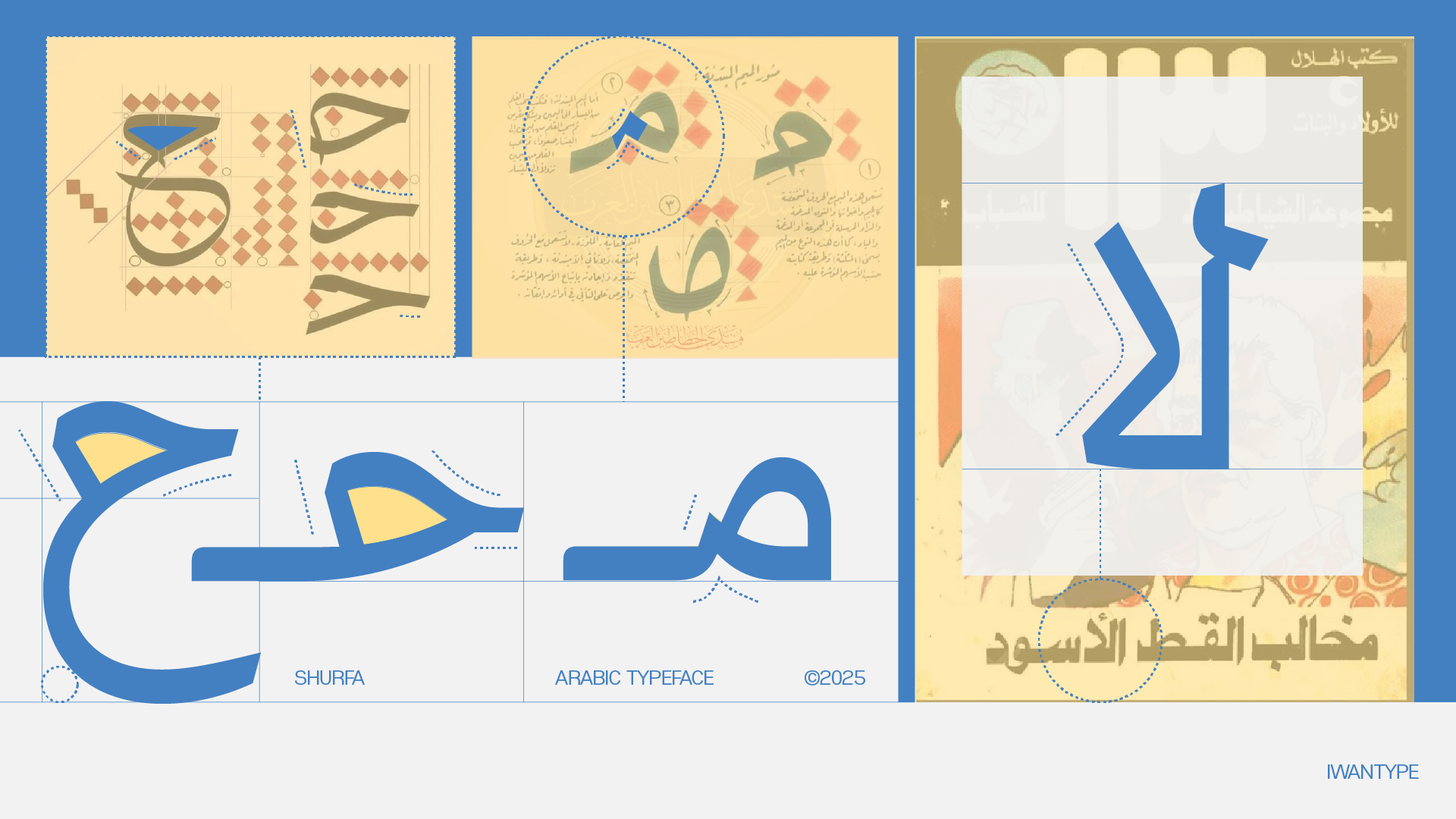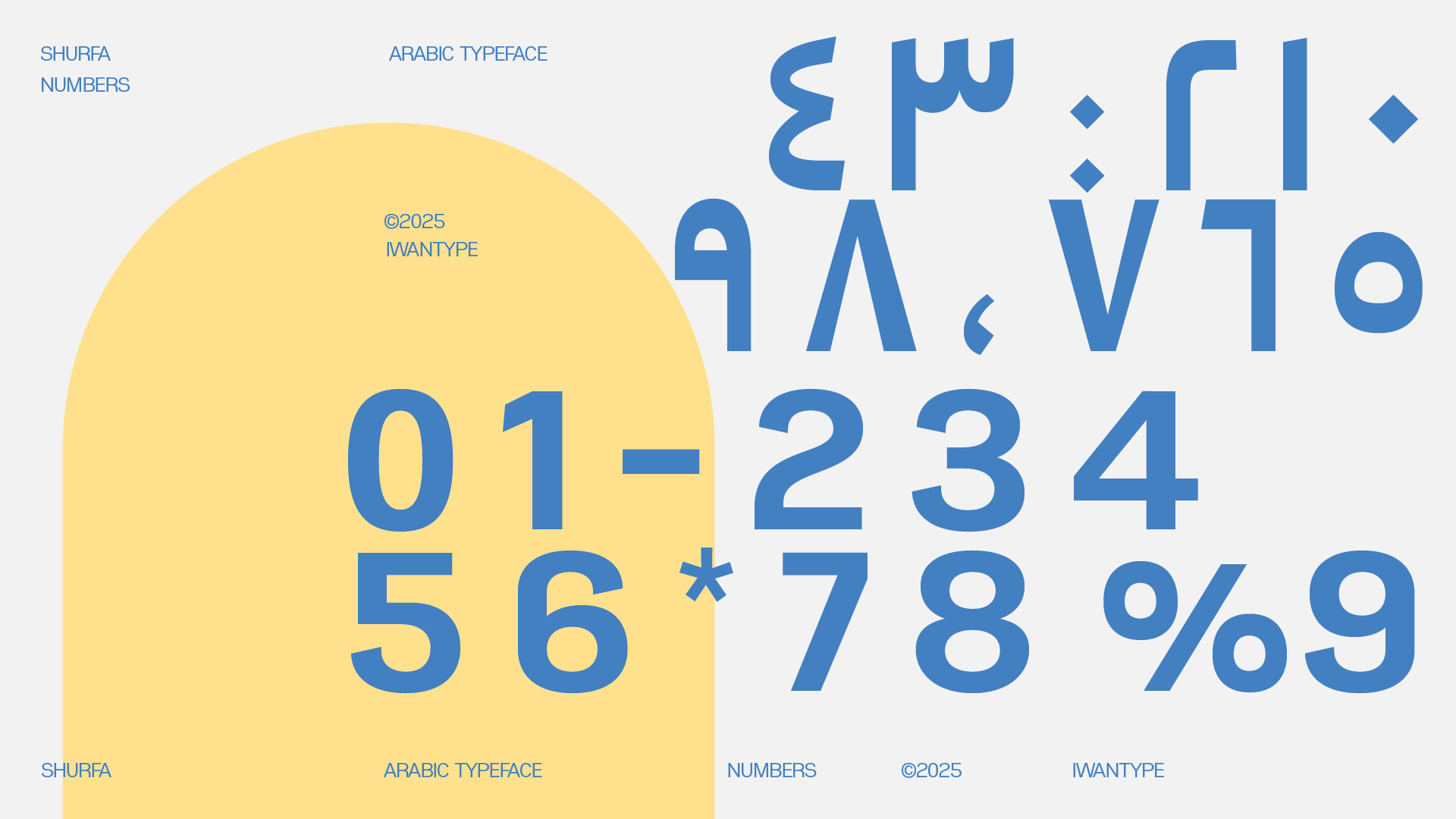
شرفة – خط عربي طباعي مبني على النسخ المسطري ومستوحى من خط الثُلث
خط «شرفة» هو خط عربي طباعي مبني على أسلوب النسخ المسطري، ومستوحى من التفاصيل والأساليب البصرية لخط الثُلث.
يتكون الخط من خمسة أوزان مختلفة تتراوح من الخفيف إلى الثقيل جدًا، ومصمم للاستخدام في العناوين، والنصوص القصيرة والمتوسطة، ومختلف التطبيقات الطباعية والرقمية.
يتميز خط شرفة بتصميم واضح ومرتكز على السطر، ويعكس دمجًا بين خصائص النسخ المسطري وبنية الثُلث.
الخط مناسب لاستخدامات التصميم الجرافيكي، وتصميم الهويات البصرية، والعناوين الرئيسية في المنشورات المطبوعة
والرقمية.